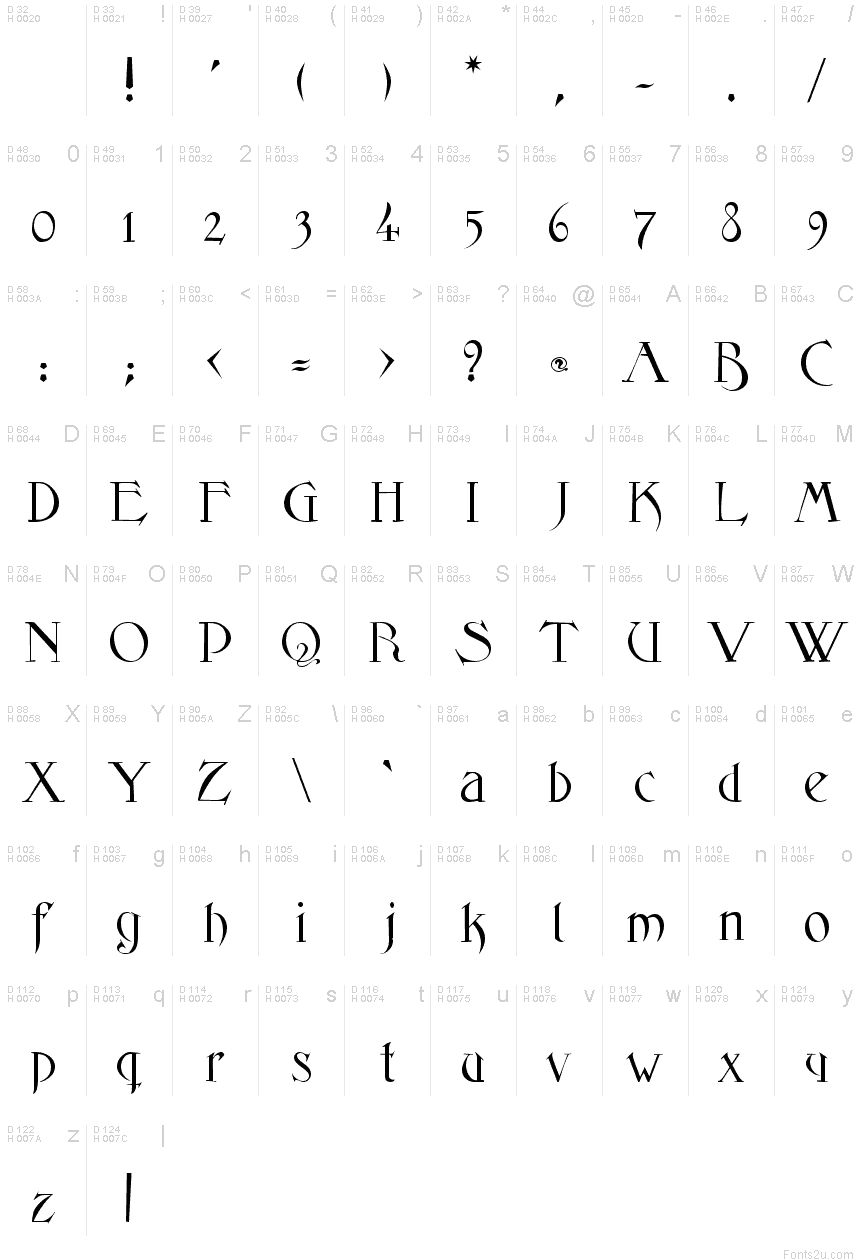
Elphinstone autorstwa Davida F. Nalle to darmowy, vintage'owy krój szeryfowy o wysokich, smukłych literach i ostrych, przypominających ostrza szeryfach, które nadają mu literackiego i nieco tajemniczego charakteru. Smukłe linie pionowe, eleganckie krzywizny i sporadyczne, strzałkowate pociągnięcia nadają mu baśniową intensywność, która natychmiast przykuwa wzrok w nagłówkach i krótkich tytułach, zachowując przy tym doskonałą czytelność w średnich rozmiarach.
Dzięki Elphinstone Twoje projekty zyskują nutę mrocznej elegancji, która świetnie pasuje do okładek książek, map fantasy, logotypów butików, etykiet win, plakatów tematycznych, zaproszeń czy wystaw historycznych. Ten darmowy font najlepiej prezentuje się, gdy ma przestrzeń – użyj go w większym rozmiarze i zestaw ze spokojnym, humanistycznym krojem bezszeryfowym, aby jego wyraziste detale budowały nastrój, nie przytłaczając układu.